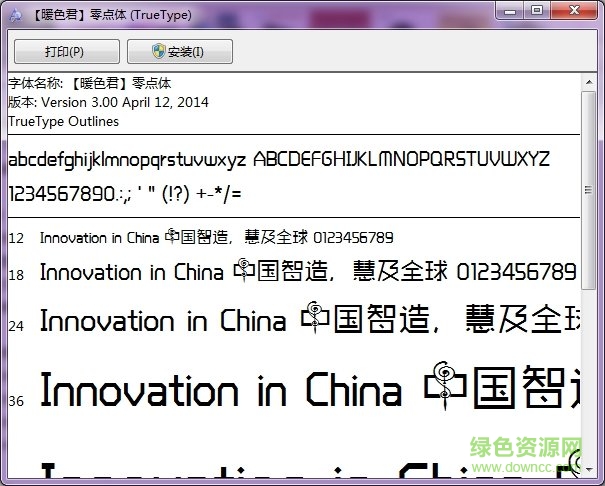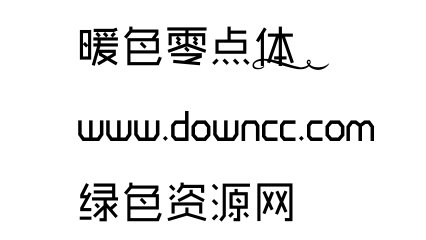
零點體字體
零點體是暖色君推出的一款藝術字體,在合體字體的基礎上添加了各種不同的修飾,讓文字變得個性十足,比起端正的宋體和楷書,顯得十分活潑,喜歡的歐陽就來綠色資源網下載吧!
暖色君零點體字體介紹
暖色零點體是由暖色君制作分享的卡通字體,字體間又裝飾上了漂亮的花紋,更加具有藝術感,將黑體字體進行重新設計,給人舒適搶眼的視覺效果,可以廣泛運用于書面設計、文字印刷、海報設計等場合。